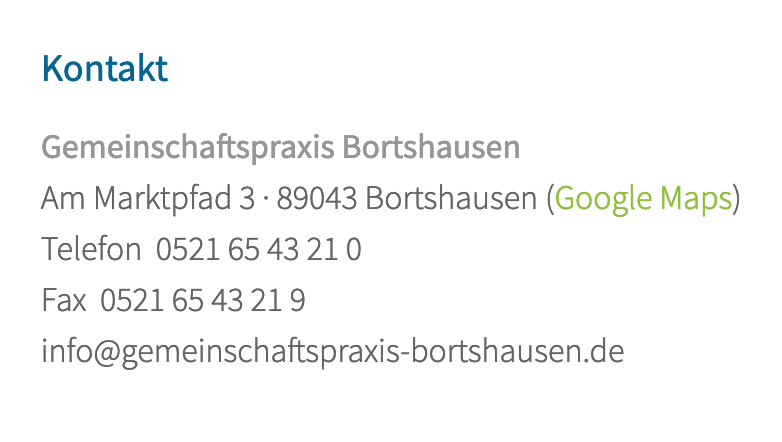
Kennzeichnung einer Faxnummer per Symbol?
Zumal aktuelle Multi-Funktionsdrucker, haben diese auch eine Fax-Funktion sich äußerlich von solchen ohne Faxfunktion nur durch die RJ11.Telefonbuchse und eine Zifferntastatur unterscheiden. Einen Hörer sucht man da auch vergeblich
Ein Fax-Gerät ist eigentlich nur ein Drucker, der über die Telefonleitung mit Daten zum Drucken gefüttern werden kann.
Nicht daß das zum Thema beiträgt, aber ein Faxgerät ist etwas ganz anderes als ein Drucker. Keiner meiner bisherigen Drucker konnte Dokumente einlesen, und keiner benützte eine normierte Übertragung. Das eine ist ein Drucker, das andere ... nicht.
Dialog zwischen Data und Pulaski in Star Trek: The Next Generation (Staffel 2, Folge 1):
Pulaski: "Data, Dada, wo ist der Unterschied?"
Data: "Das eine ist mein Name, das andere ... nicht."
Nicht daß das zum Thema beiträgt, aber ein Faxgerät ist etwas ganz anderes als ein Drucker. Keiner meiner bisherigen Drucker konnte Dokumente einlesen, und keiner benützte eine normierte Übertragung. Das eine ist ein Drucker, das andere ... nicht.
Grundsätzlich hast Du natürlich recht - aber es geht hier ja nicht darum, was Du als Faxbesitzer damit machen kannst, sondern um die Funktion, die das Faxgerät demjenigen bietet, der die Kontaktinformation bekommt und nutzen soll. Und für den ist es letztendlich nur ein Drucker, der über die Telefonleitung angesprochen werden kann. Ich hoffe, Du verstehst den auf diesen Aspekt reduzierten Blickwinkel.
Übrigens werden auch die Druckdaten in einem definierten Format übertragen, es ist nur ein anders als beim Fax.
Zur Diskussion "Spiegelt das Faxsymbol die dahinter stehende Technik wieder?":
Ich halte sie nicht für zielführend. Weiter oben schrieb ich bereits, dass es meiner bescheidenen Ansicht nach im Wesentlichen darum geht, ob ein Symbol gut verständlich ist und nicht, ob es die Technik eines Gerätes korrekt wiederspiegelt.
Unabhängig davon habe ich nochmal die Argumente von Martin und Þorsten für einen weiteren Entwurf aufgegriffen, siehe Anhang.
Diesmal ganz ohne Symbole.
Abheben des Namens durch Abstand.
Einzeilige Adresse.
Bewußt langes Etikett "Telefon" statt "Tel", damit die Nummern keinen Block bilden.
Zum Vergleich direkt darunter: mit Symbolen.
Den Namen könnte man zusätzlich noch mit anderen typografischen Mitteln abheben, vielleicht Versalien, eine Kursive, ...?
Aber das sind Nebensächlichkeiten.
Weiterhin könnte ich von meiner bisherigen Praxis, der Hervorhebung von Links durch Farbe, im Bereich Kontakte abweichen. Aber ich scheue diese Inkonsistenz gegenüber den anderen Bereichen der Site.
Reizen würde mich ja bei der eingebetteten Karte eine Reduktion der "knalligen" Elemente, wie z.B. das rote "Fähnchen". Aber meines Wissens sind solche Manipulationen nur gegen Bezahlung des Dienstes möglich.
Das mit den langen Etiketten sieht doch super aus!
Das mit der Karte würde ich lösen, indem ich selbst eine Karte zeichne und diese dann als Bild zu Google Maps linke.
Abheben des Namens durch Abstand
Das finde ich störend. Es handelt sich ja nicht um eine Überschrift. Und die Textmenge ist doch so überschaubar, dass es keiner Heraushebung bedarf.
Sachlich ist es ein übergeordneter Punkt und es folgen 4 alternative Arten für Kontaktmöglichkeiten.
Dann noch lieber in derselben Schriftgröße und ohne zusätzlichen Abstand, sondern halbfett.
Nachtrag: Das würde ruhiger wirken und gleichzeitig mehr Klarheit schaffen.
vor 3 Stunden schrieb Ibu:
Sachlich ist es ein übergeordneter Punkt
Ja, schon. Wobei das Wort »Kontakt« in der Hierarchieebene ja noch darüber steht. Und dann frage ich mich schon, ob man die zweite Hierarchieebene mit dem Namen bei der geringen Textmenge wirklich eigens auszeichnen muss.
Warum ist die Emailadresse farblich hervorgehoben, die ebenfalls anklickbare Telefonnummer aber nicht? Obwohl die den Hinweis »Mich kannste auch anklicken« viel eher gebrauchen könnte? Lass doch die Farbe generell weg! Dass man Emailadressen anklicken kann, weiß nun wirklich jeder. Andererseits werden wenig IT-affine Nutzer mit anklickbaren Telefonnummern (am Desktop) ohnehin wenig anfangen können. Am Telefon toucht man hingegen gewohnheitsmäßig auf alles mögliche. Entweder die Telefonnummer wird dabei dann kopiert oder es geht eben gleich die Wähler-App auf, ob nun mithilfe der Website oder nicht.
Kontakt halte ich, wenn da nicht so viel Info steht, auch für eher überflüssig. Arztpraxis Sowieso in fett, ohne Leerzeile, ohne sonstige Überschrift → schon sieht die Sache sehr viel aufgeräumter aus.
Ist das dynamische Einbinden einer Google-Map ohne vorherige Einwilligung des Nutzers in Deutschland noch datenschutzkonform?
Als die Nutzung von Emoticons "modisch" wurden, gab es meiner Erinnerung nach Versuche, im Internet längere Informationen so zu kodieren. Das war aber außerhalb der Chat-Medien nicht von Dauer, zumindest nicht in meiner Blase.
Ist jetzt exakt unser hiesiges Problem, aber ich denke, dass ich nur dann von einer gewohnten und erwarteten Informationspräsentation abweichen würde, wenn ich mir davon einen Mehrwert verspreche.